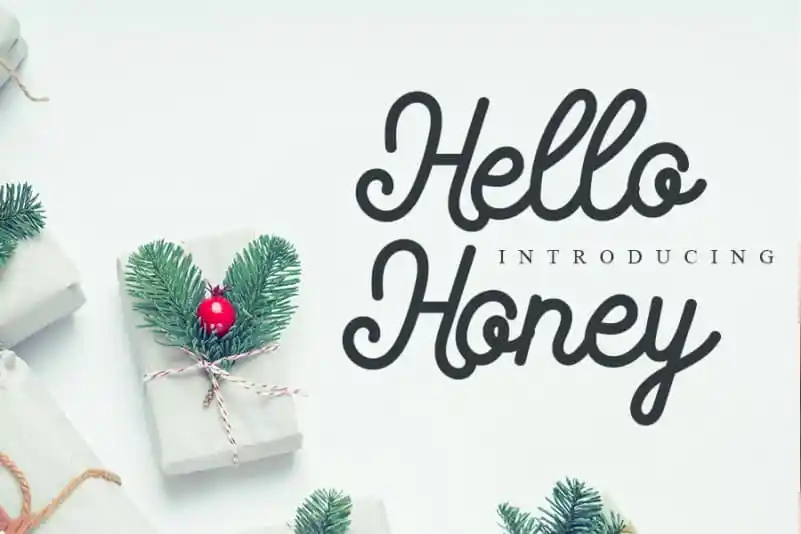
Hello Honey Handwritten Font – Download Grátis
A fonte ‘Hello Honey Handwritten Font’ é perfeita para aqueles buscando uma escrita criativa e contemporânea que mantém influências classicamente elaboradas. Com seu estilo único, essa fonte se adapta com facilidade a diversas idéias de arte útil, como cartões de visita e títulos, bem como decoração em geral. Suas características fluidas e suavemente dinâmicas fazem dela uma opção ideal para designers que valorizam tanto o clássico quanto a modernidade. Esta fonte é especialmente adequada para aqueles buscando adicionar um toque diferenciado à sua proposta de design, seja em cartazes, rótulos de embalagens ou qualquer outra maneira criativa. Em uma era onde os designs mais elaborados são muitas vezes vistas como caros e desacreditados, ‘Hello Honey Handwritten Font’ oferece a oportunidade de criar um equilíbrio elegante com uma sensação leve e moderna. Seja para o seu site pessoal, projeto de marca ou qualquer outro trabalho em que você queira expressar individualidade, essa fonte é uma escolha inteligente.